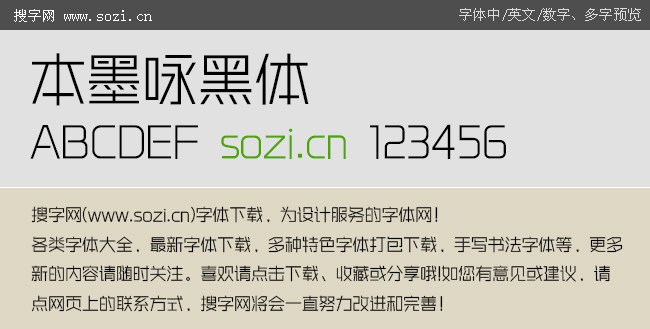
本墨詠黑體
搜字網(wǎng)提供一款本墨詠黑體中文藝術(shù)字體下載,本墨詠黑字體是本墨字庫(kù)最新推出的一款造型簡(jiǎn)簡(jiǎn)單大方的中文簡(jiǎn)黑體,該字體結(jié)構(gòu)均衡,有著極佳的觀賞體驗(yàn),字形正直優(yōu)雅,且字體庫(kù)完整。適用于書籍設(shè)計(jì)、報(bào)紙標(biāo)題、畫冊(cè)設(shè)計(jì),網(wǎng)頁(yè)設(shè)計(jì)等應(yīng)用。